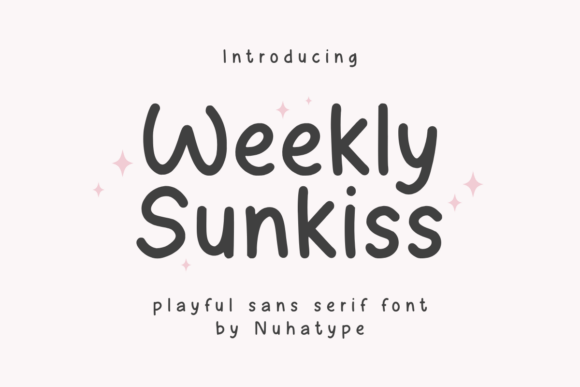
Weekly Sunkiss
適切なデザイン要素を見つけるのは難しい場合がありますが、Weekly Sunkissは作品を即座に引き立てる優れたコレクションを提供します。
POD(オンデマンド印刷)製品、結婚式の招待状、またはソーシャルメディアのグラフィックを作成している場合でも、Weekly Sunkissは理想的です。